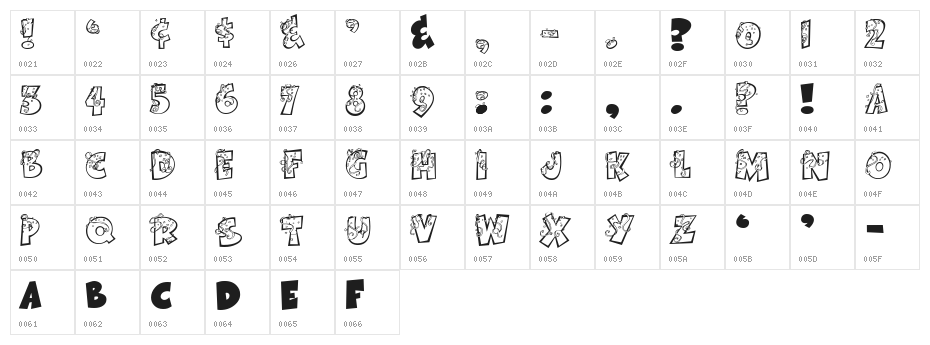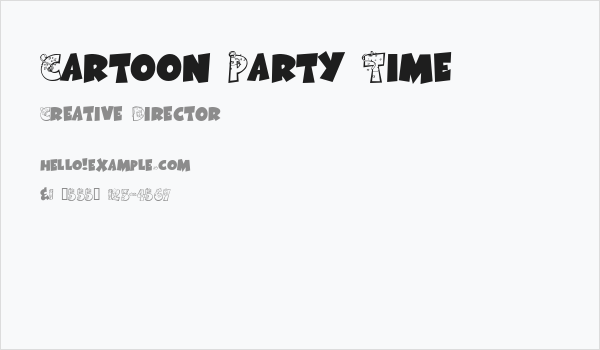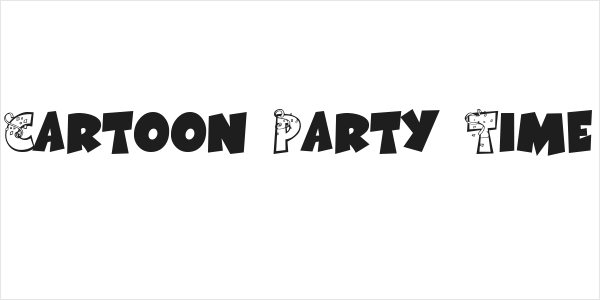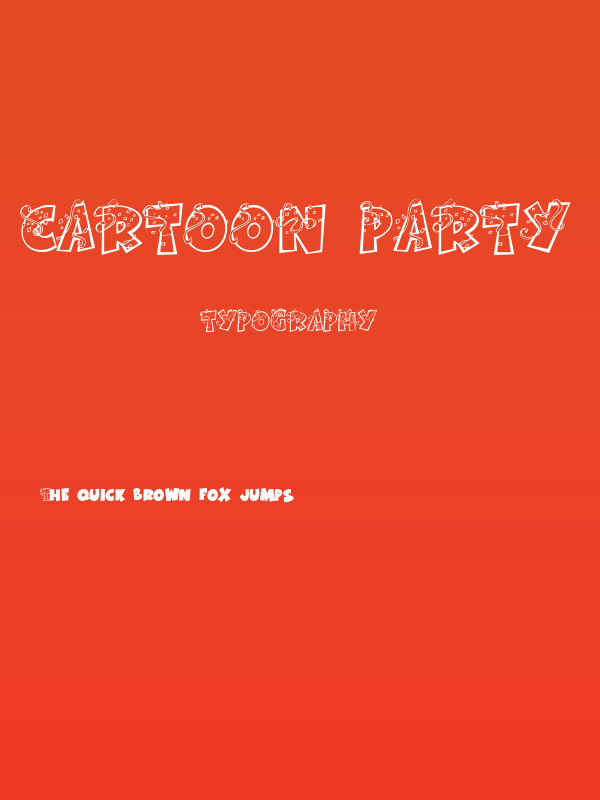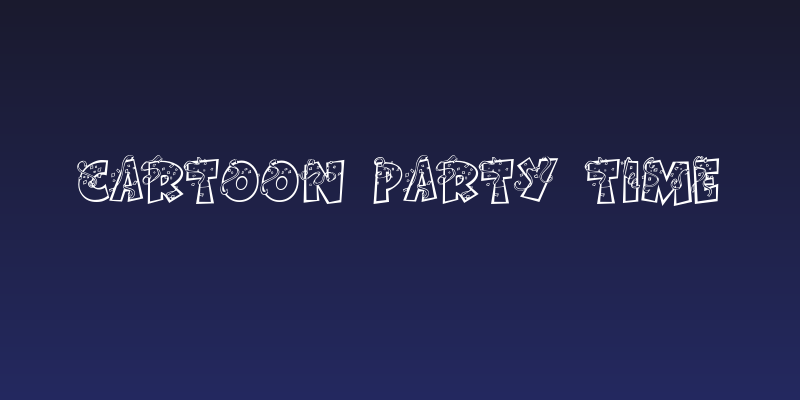
Cartoon Party Time Font
✎ Outline
| 整体风格 | Cartoonish, Fun, Whimsical |
| 推荐项目 | Ideal for children's books, party invitations, comic strips, and playful branding. |